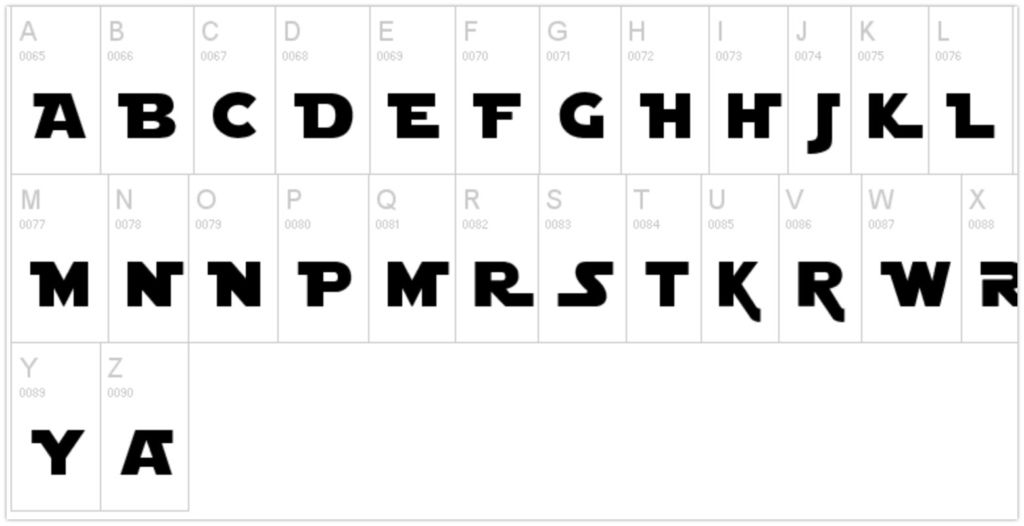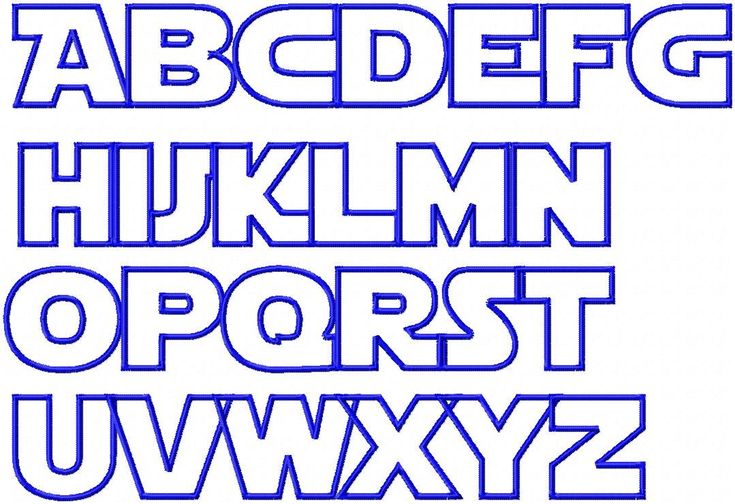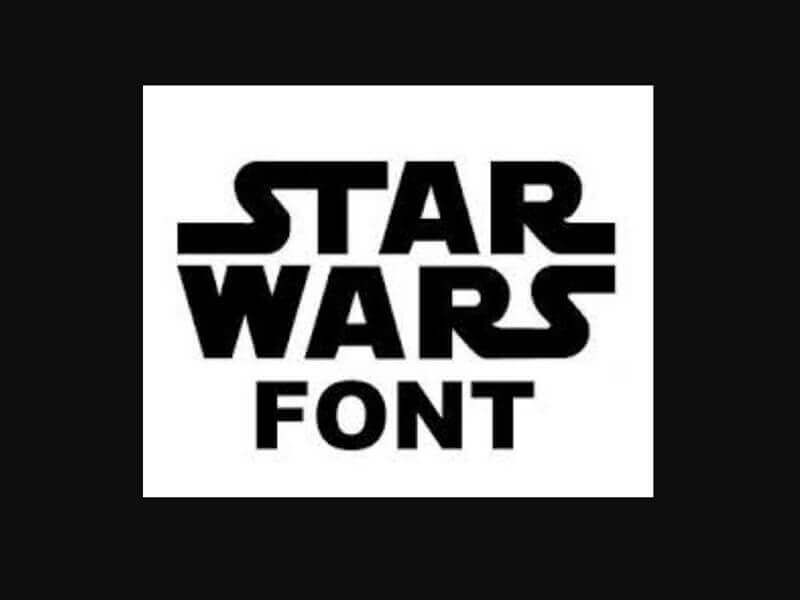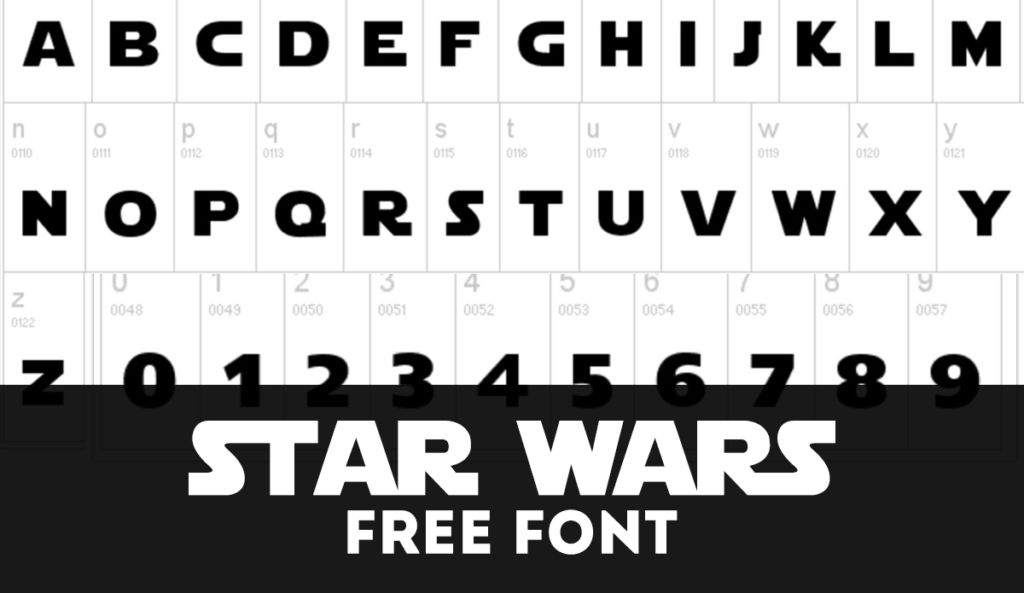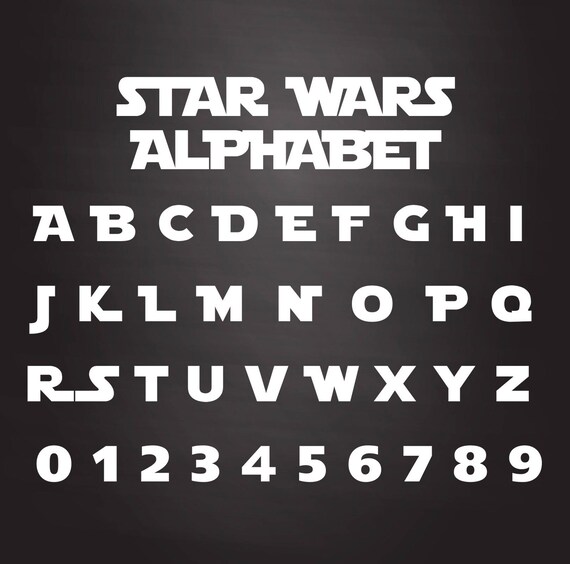
Этапы работы над логотипом на примере кейса с собачками — Дизайн на vc.ru
Рассказываю про работу над проектом Маши Морозовой — грумера из Санкт-Петербурга: от брифа до результата и передачи файлов, как я пришла к итоговой картинке и причем тут Чубака.
Логотип для судии груминга chewie grooming
Структура:
- знакомство и брифинг: обсуждение пожеланий и нюансов, постановка ТЗ;
- мудборд;
- скетчинг;
- эскизы;
- доработка эскиза, дополнительные версии и презентация на носителях;
- дополнительные задачи по проекту;
- впечатления и выводы;
Знакомство и брифинг
Мы с Машей познакомились в январе этого года, она собиралась открывать кабинет и искала исполнителя на дизайн.
Название ее бренда chewie grooming (Чуи груминг): Чуи от Чубаки из вселенной Star Wars. Идея в том, как заросшая собачка превращается в аккуратно подстриженную после груминга. Поверхностно задача стояла такая: «У меня уже был первый вариант визиток, и изначальный смысл не поменялся, но хочется поменять цвета и стилевое оформление, чтобы было ярко, сочно и стильно».
Я отправила клиентке на заполнение бриф: анкету по задаче. Маша заранее подготовила примеры логотипов и стилей, которые нравятся: детализированные и с юмором. Я тоже подготовила примеры на обсуждение: логотипы с разной степенью детализации, чтобы понять, чего клиентка ожидает от результата. Для уточнения деталей мы созвонились: обсудили заполненный бриф, примеры и обговорили нюансы.
Старая визитка и примеры логотипов с собаками
Задача
Сохранить образ и семантику из старого логотипа. Собака должна быть обязательно. Не использовать образ пены. Стиль: иллюстративный, с запоминающимися деталями.
Челлендж:
В логотипе одновременно нужно показать и заросшую собаку, и ухоженную, как на старой визитке. При этом она должна выглядеть как настоящая собака и не отталкивать.
Мудборд
Мы согласовали ТЗ, Маша заплатила предоплату 50%, а я приступила к работе. Первым делом составила мудборд (доску настроения) по четырем категориям: колористика, графические образы, фотографии и типографика.
Колористика
Клиентка четко обозначила желаемую гамму. Аргументы в пользу цветов: работа в таком окружении будет комфортной, также Маша в будущем планирует неоновое оформление стен, а желтый и сиреневый неон выглядят не так агрессивно как яркие оттенки.
Мудборд: цветовая гамма: графитовый, желтый, сиреневый
Графические образы
Сюда сложила не только графику, но и фотографии. Я старалась понять, какие эмоции, детали, приемы и элементы хочу использовать в знаке. Мне в душу запали подмигивания и высунутый язык. Я решила, что эти эмоции передают необходимый задор и позитив.
Мудборд: акцент на подмигивания и высунутый язык
Фотографии
Я взяла фотографии из профиля Маши в соцсети и подобрала на стоках фотографии собак, которые схожи по стилю и настроению. Этот раздел при необходимости поможет клиенту с подбором фотоматериалов в дальнейшем. Мне понравилась фотка собаки в полотенце, я подумала: «О, похожа на звезду в салоне красоты».
Я построила эскизы на этом образе, чтобы передать качество и уровень заботы. Но об этом попозже.
Мудборд: фотографии клиентки и со стоков
Типографика
Я подбирала геометрические шрифты на основе типографики из примеров. Сразу понравились массивные буквы: чистые, но с характером. Они подошли бы к дерзкому настроению.
Мудборд: акцент на геометрические шрифты
Скетчи
Мудборд составлен, вектор ясен, а значит пора делать скетчи. Я старалась подбирать отличающиеся породы собак, чтобы понять анатомию. Искала ракурс, который подойдет лучше, думала, как с этого ракурса передать эмоцию. Здесь же я попробовала примерить на собак полотенце, кепки и очки, которые могли бы передать игривость и дерзость. В итоге я взяла три образа для стилизации под логотип и приступила к отрисовке эскизов.
Карандашные наброски собак
Эскизы
В каждом эскизе я постаралась выделить одно настроение.
В первом варианте максимум задора и игривости, во втором — дерзости, а в третьем в первую очередь читается доброта и забота. Полотенце в каждом варианте создает разную семантику и подкрепляет эмоцию. В первом — это сползшее полотенце, потому что песелю не сидится на месте, во втором — как бы небрежно накинутое полотенце после процедуры, а в третьем — бережно укутанное вокруг и выложенное в форме сердца.
Три эскиза логотипа
Я записала для клиентки видео, на котором объяснила каждую задумку. С интересом ждала, что она выберет, потому что мне нравились все варианты и я была готова продолжать работу с любым из них. Маша в итоге отдала предпочтение дерзкому псу в очках. Его и взяли за основу. А еще именно в этом варианте получилось гармонично совместить длинную шерсть Чубаки и аккуратно подстриженную сбоку. Клиентке настолько понравилась идея со знаменитостью, что она предложила заменить полотенце на воротник куртки: добавить стиля так сказать.
От третьего варианта утащили уши и силуэт сердца.